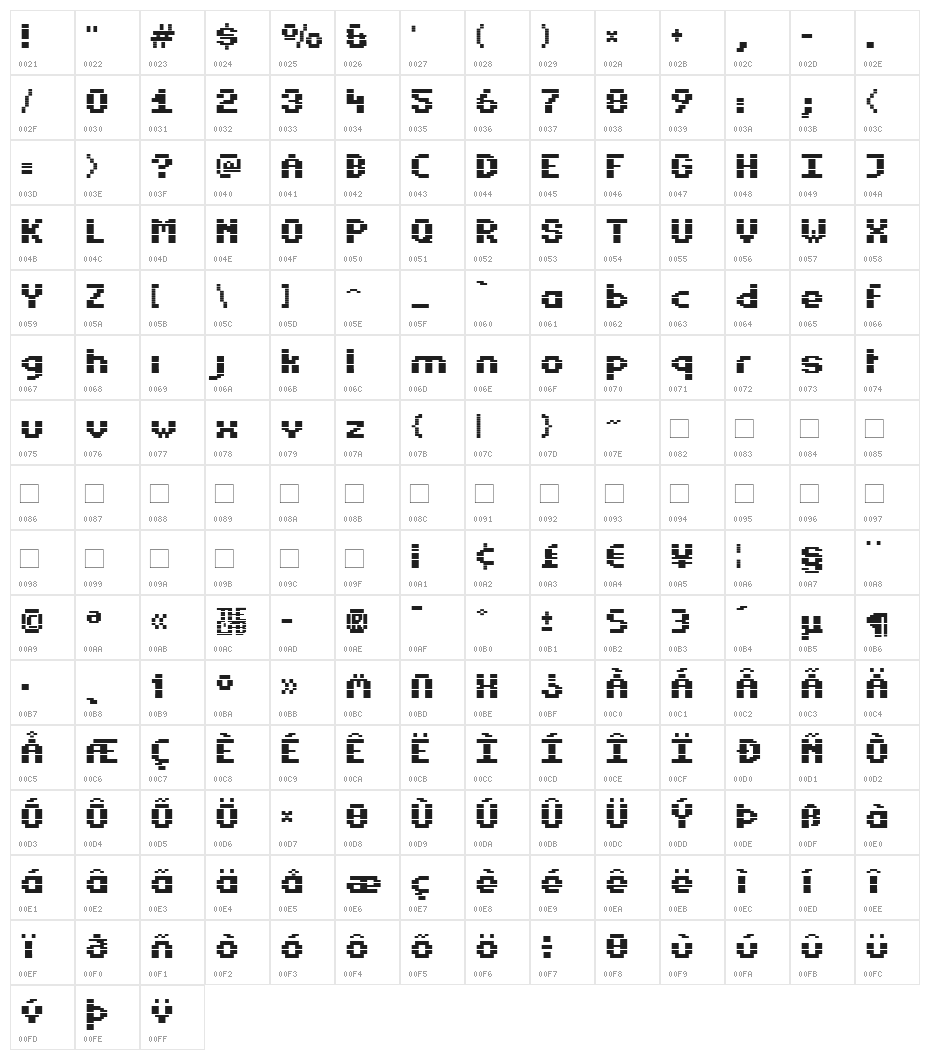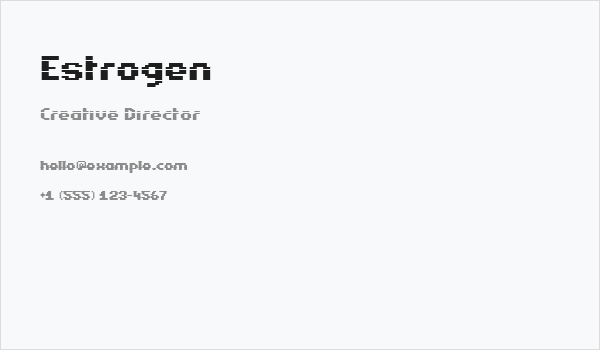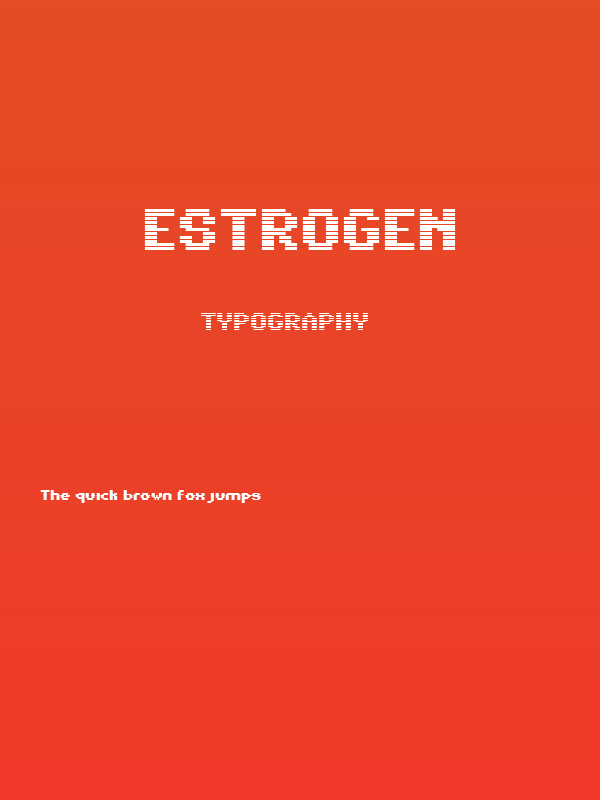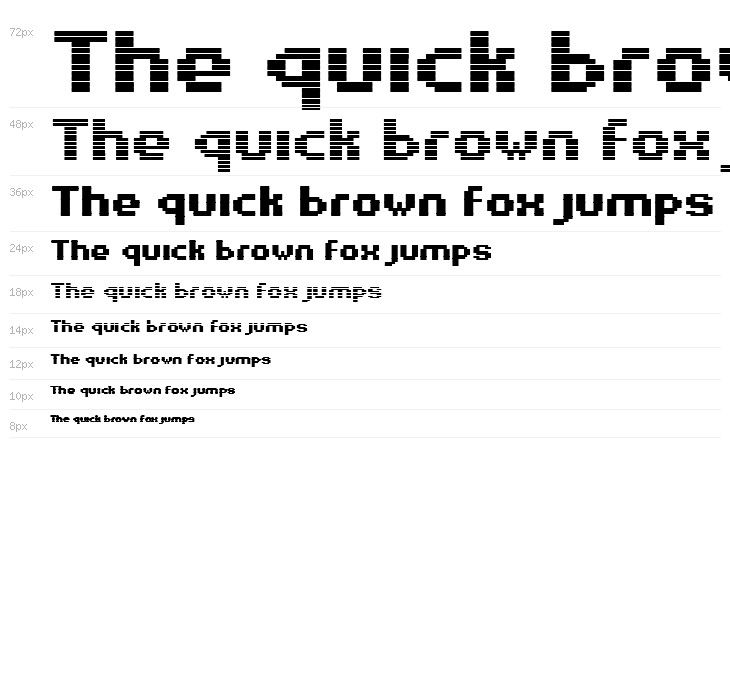
Estrogen Font
| Kategorien | Pixel |
| Gesamtstil | Retro, Digital |
| Anwendungsfall | Logos, Headlines, Posters |
| Vorgeschlagene Projekte | Ideal for digital art projects, retro-themed designs, video game graphics, or any creative work that requires a unique, tech-inspired typeface. |